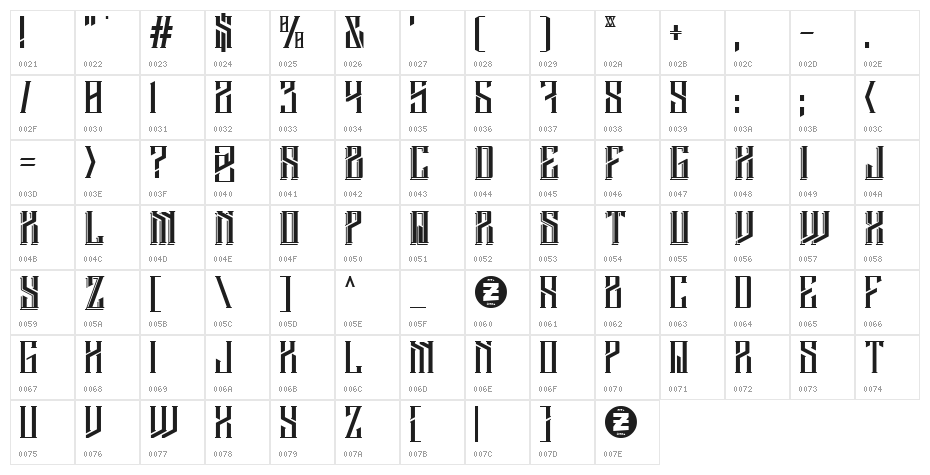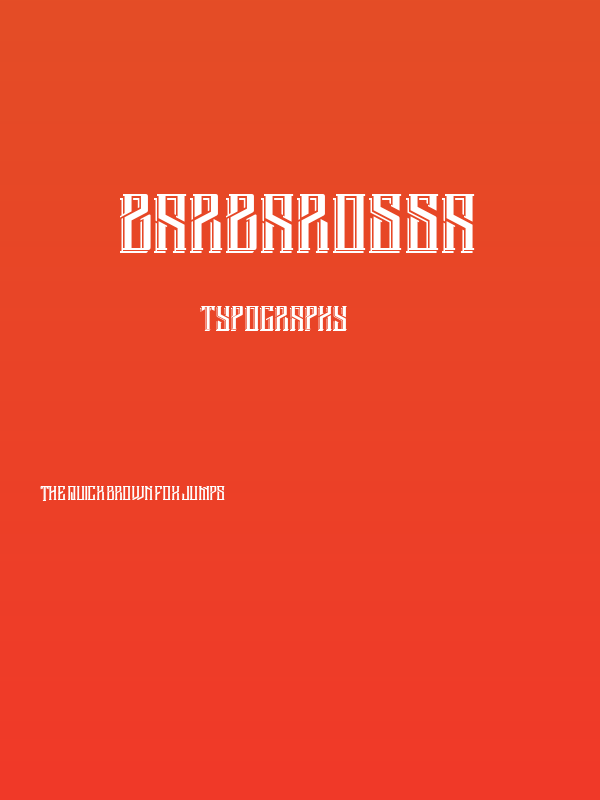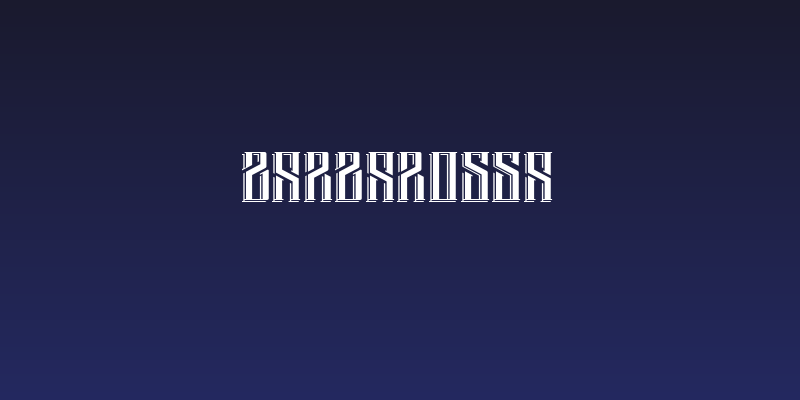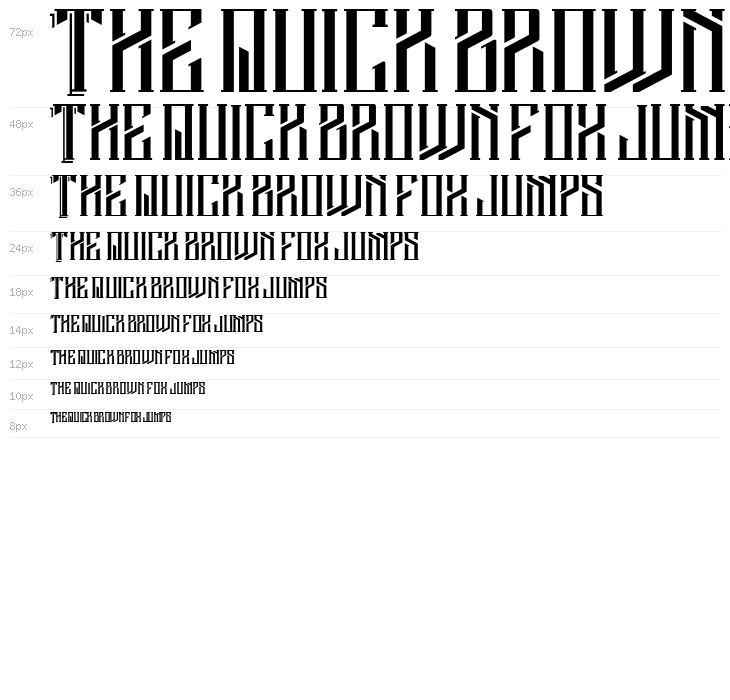
Barbarossa Font
✎ Gothic
| 分类 | Gothic |
| 宽度 | Condensed |
| 整体风格 | Modern Gothic |
| 推荐项目 | Ideal for projects that require a dramatic and eye-catching typeface, such as posters, album covers, branding for edgy or alternative brands, and video game titles. |